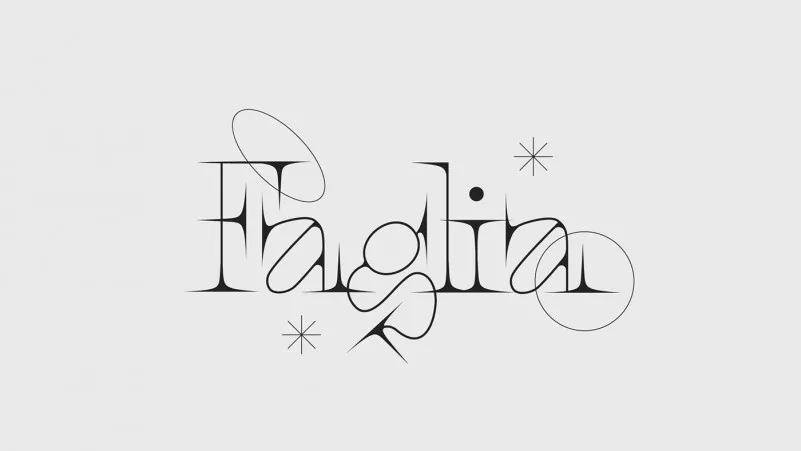
Esta fonte serif é uma atraente mistura entre os mais recentes designes criativos e o charme clássico do estilo serif tradicional. Conheça “Faglia Font”, uma escolha inteligente para projetos exclusivos que valorizam o equilíbrio elegante de um tipo serif com as personalidades quirkys das letras mais atemporais. Suas linhas afiadas e arredondamento sofisticado permitem criar designs memoráveis tanto em impressões como em superfícies, sejam elas paredes, logotipos ou etiquetas. É uma escolha versátil para criações diversas que incluem design de casamentos, embalagens de produtos, cartões de lembrança, e até mesmo a arte digital das suas fotografias. Com “Faglia Font”, seu trabalho pode ser mais do que apenas texto; ele se torna um elemento artístico perfeito para qualquer projeto visual.